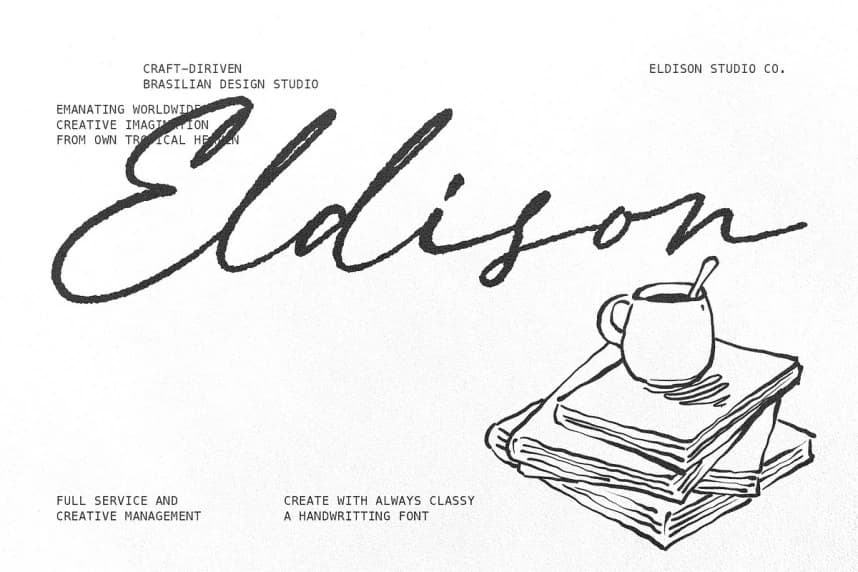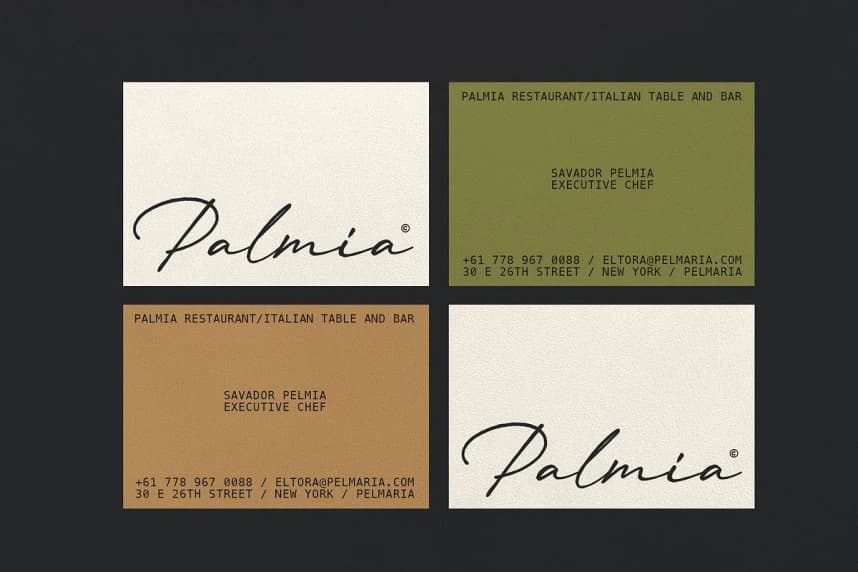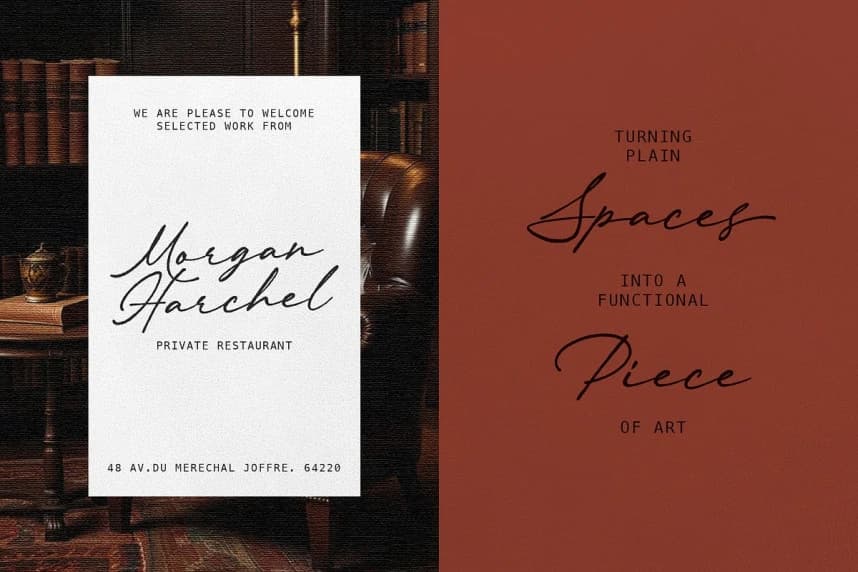
Always Classy Font
Always Classy Font, yaratıcı projelerinize zamansız zarafet ve doğal çekicilik katmak üzere tasarlanmış sofistike bir el yazısı script fontudur. Modern kaligrafi ve rafine imza yazı stilinden ilham alan bu font, akıcı ve yumuşak çizgileri bir araya getirir.
Always Classy Font, yaratıcı projelerinize zamansız zarafet ve doğal çekicilik katmak için tasarlanmış sofistike bir el yazısı fontudur. Modern kaligrafiden ve zarif imza hatlarından ilham alan bu font, akıcı çizgileri bir araya getirir.